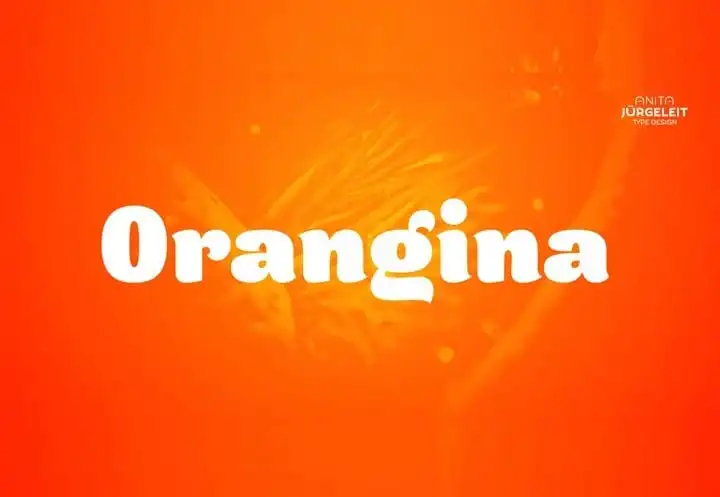
A Orangina Display Font é uma fonte de exibição com traços muito grossos, mas ainda possui uma forte contraste. Esta foi criada e compartilhada pela designer Anita Jürgeleit. Uma vez mais, durante o inverno? Não há melhor momento para lançar um fonte tropical em meio a tal cenário. Todos os visuais são azuis gelados ou brancos. A trilha de Natal está por toda parte e o ‘Jingle Bells’ toca incessantemente! Mas aqui é uma boa notícia: grossas, vibrantes, cítricas e cheias de vitamina visual para combater a friza das tempestades de chuva. Salte da escuridão e dissolva os gelos frígidos entre você e suas criações com estas formas lindas do Letra, levando seu design ao nível excepcional que se estende acima das nuvens. Esta fonte é uma ótima opção para tornar seus designs mais atraentes em dias chuvosos. Não importa o tema de sua peça, as formas vibrantes e cítricas da Orangina Display Font garantirão um toque especial à sua criação, elevando-a acima das nuvens. Talvez não esteja tão brincando quando diz que esta é uma excelente fonte!